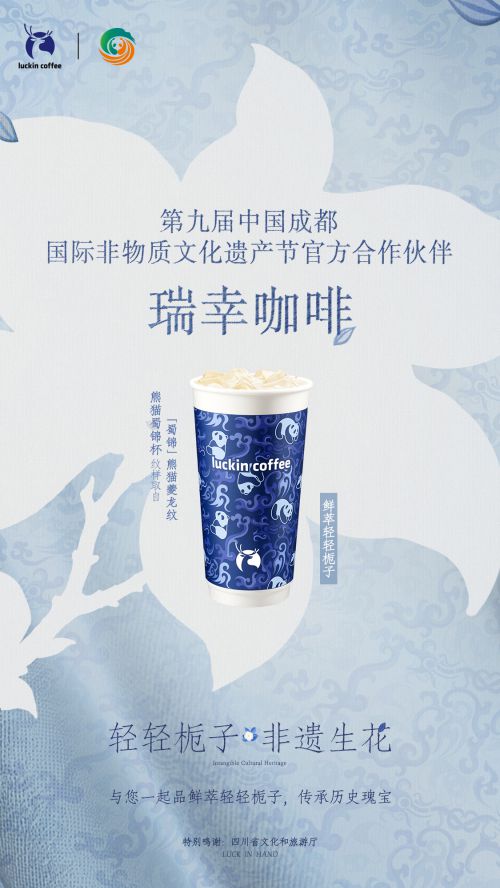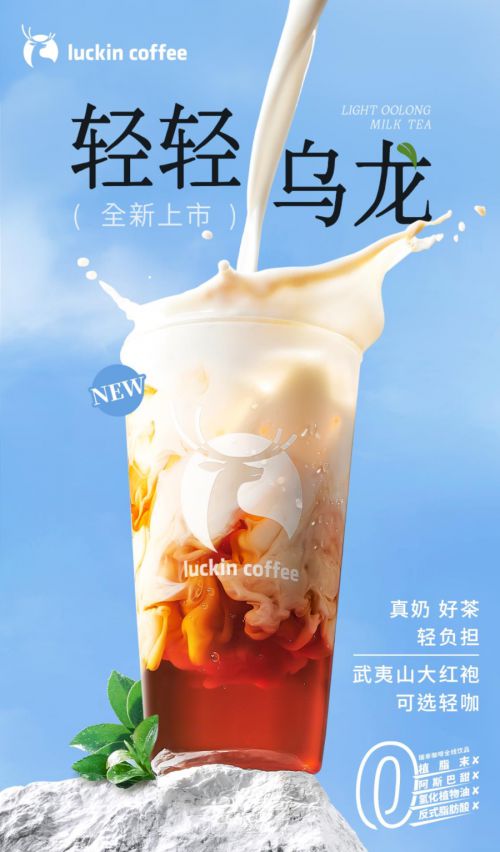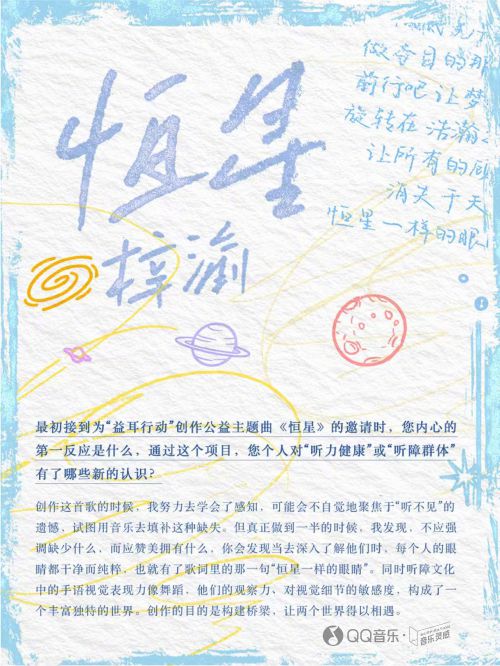
点字典宋
点字典宋是一款具有独特风格的宋体字体。它在传统的宋体字形基础上,巧妙地融入了“点”的元素,使得笔画的收尾或转折处呈现出一种灵动、跳跃的视觉特征,仿佛是由细小的点连接而成。这种设计赋予了字体一种别样的韵味,既保留了宋体的清晰易读,又增添了艺术的趣味性。 点字典宋笔画简洁清晰,字形风格典雅工整,严肃大方,字形端正。